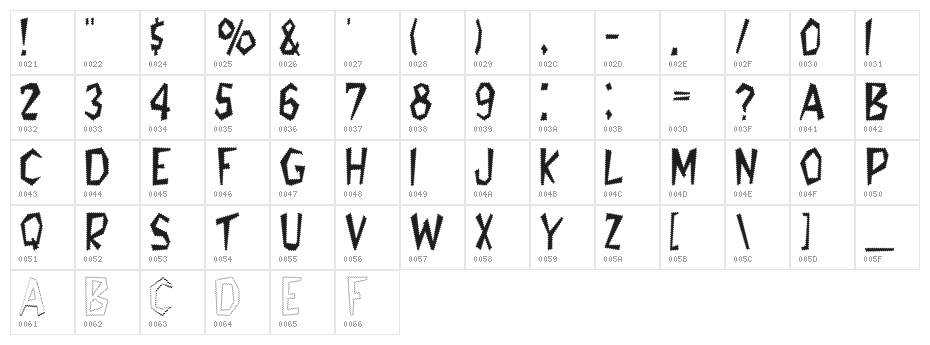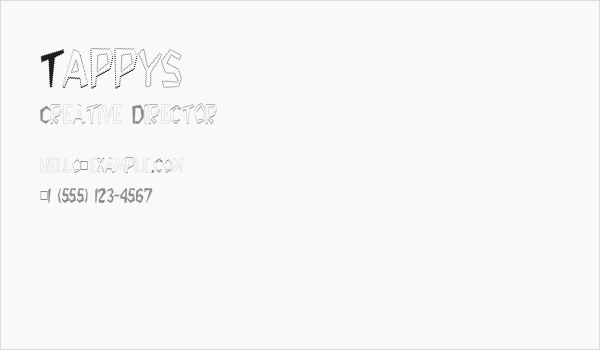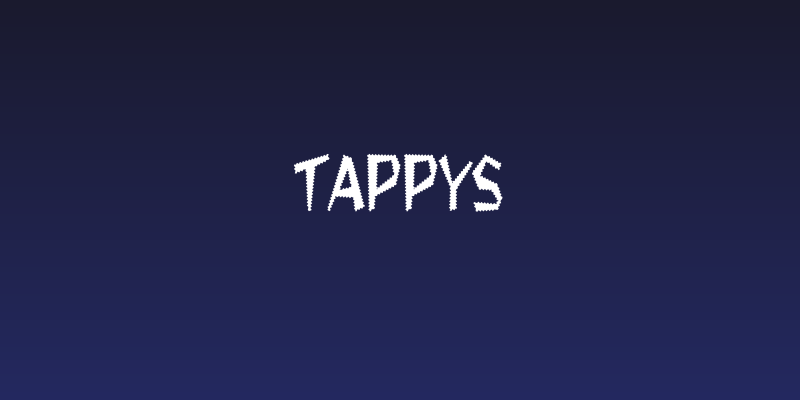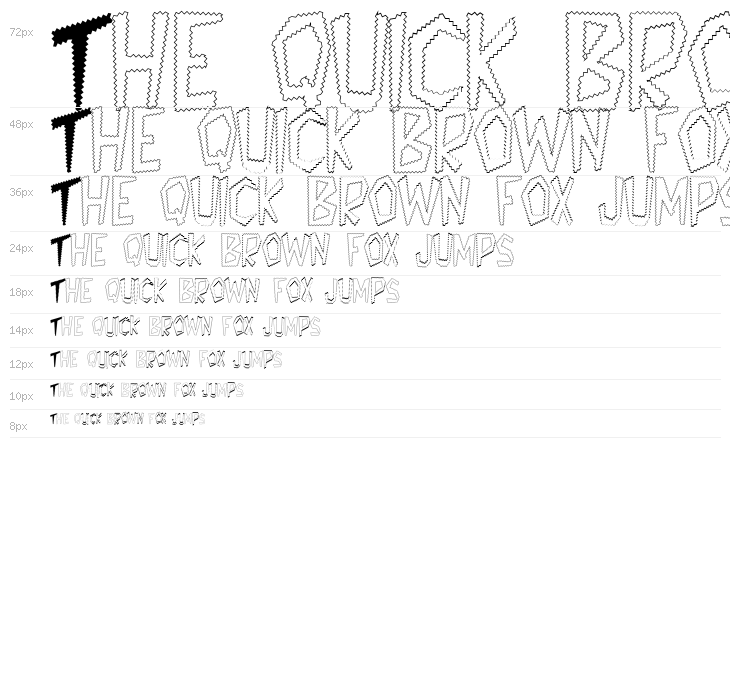
Tappys Font
✎ Outline
| Progetti proposti | Ideal for creative projects such as posters, album covers, and branding that require a bold and energetic typeface. |